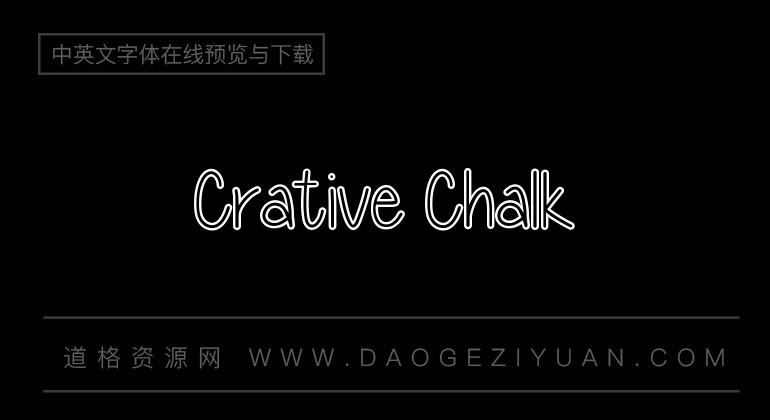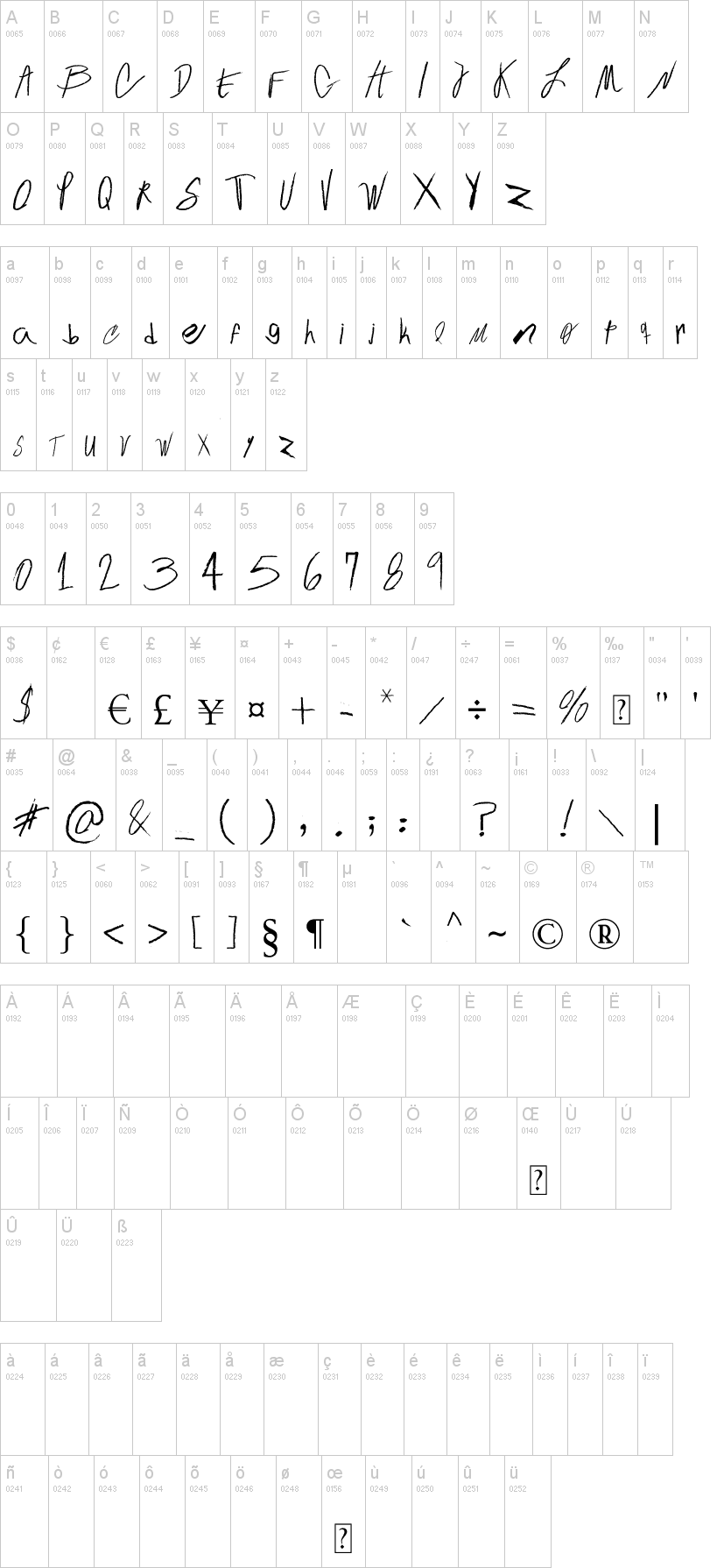
Creative Chalk 是一款由英国设计师Matthew Welch创作的手写字体。它具有温暖的质感,把涂鸦的自由感和现代感结合在一起,让文字有趣又有活力。它的特点是把涂鸦的自由感和流畅的线条结合在一起,使文字看起来更有活力,更有趣。它还有一种细节感,把细节和细节处理得非常好,让文字看起来更加生动。内容介绍
Crative Chalk是一款非常不错的手写艺术字体,具有很好的视觉感,适合于文化类的宣传设计、商业类品牌的广告和产品包装设计以及个性化文字排版等较多场景。